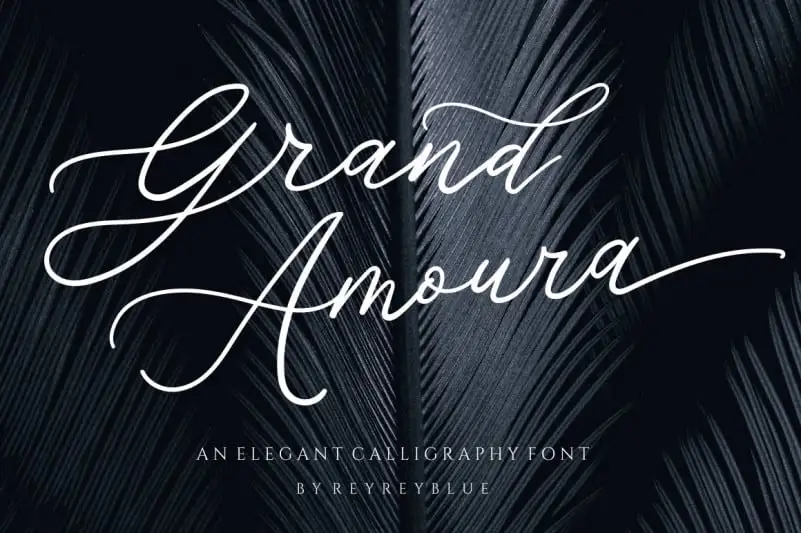
Grand Amoura Handwritten Font – Download Grátis
Introduzimos a Grand Amoura Handwritten Font, uma elegante fonte de caligrafia moderna. Esta fonte é perfeita para logotipos sofisticados, embalagens luxuosas, papelaria de casamento e qualquer projeto que exija um toque delicado e elaborado de escrita a mão. Grand Amoura oferece uma ampla gama de swashes e alternativas que permitem criar seu logo ou nome com um visual personalizado, inspirado na caligrafia manuscrita. Esta fonte traz sofisticação e luxo aos seus projetos, elevando-os ao nível mais alto. Com a Grand Amoura, você pode adicionar uma pitada única e delicada a qualquer projeto, seja em sua identidade visual corporativa ou em detalhes únicos de suas publicações online. Seja para seu site pessoal, cartas de amor digitais ou até mesmo embalagens de presentes, a Grand Amoura é capaz de dar um toque especial e delicado. Aqui está uma fonte elegante que não só deixará sua marca mais impactante, mas também garantirá um toque personalizado e sofisticado ao seu trabalho.